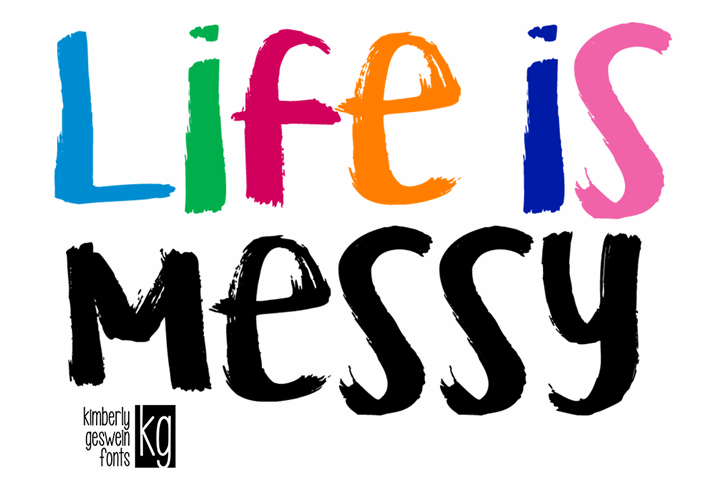
A fonte KG Life is Messy oferece uma descrição atraente para designers gráficos atemporais. Inspirada no estilo livre e desafiador dos traços livres, ela representa exatamente a vida incerta e inesperante que muitos entre nós compartilham. Para o designer Hamilton, essa font criou um espaço onde podemos expressar nossas idiossincrasias em um mundo cada vez mais organizado e linear. Como uma fonte brush, ela combina facilmente com diversos estilos de design gráfico, seja para criar letras dinâmicas e emotivas ou para adicionar personalidade aos elementos visuais. Para designers que buscam algo diferente e único na composição visual do seu trabalho, KG Life is Messy é uma excelente escolha. Com a sua versão brush, ela traz um toque de descontração ao design, permitindo criar uma ligação emocional entre o público e os elementos gráficos semelhantes à interação com a vida em si.